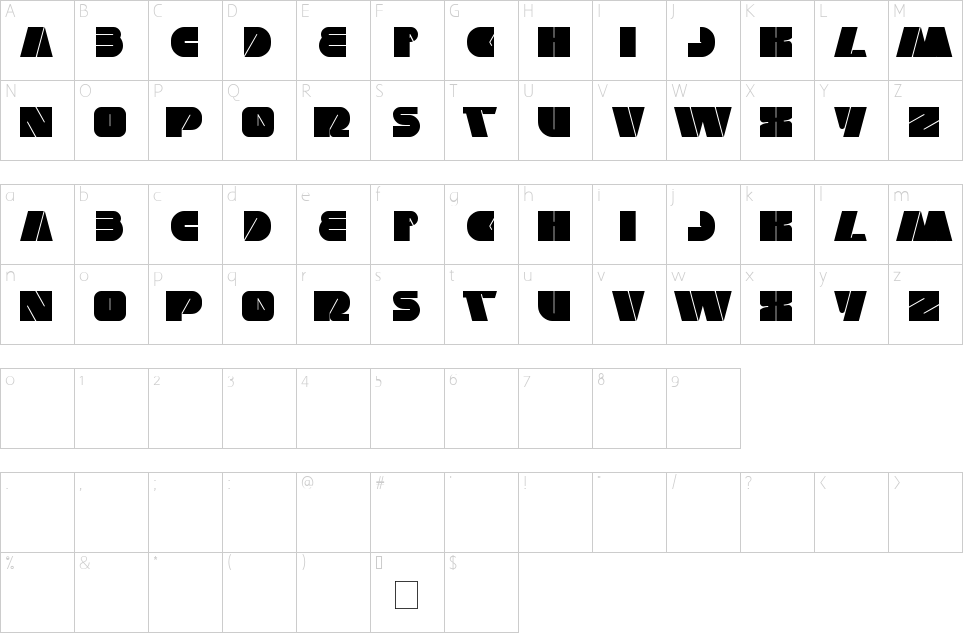
A fonte Monster Rock é uma escolha perfeita para designers que desejam um estilo poderoso e irreverente para seus projetos. Inspirada em rock, essa fonte garante um tom inovador e inconfundível em qualquer projeto. Desenvolvida pelo designer desconhecido weknow, Monster Rock é atualmente uma das fontes mais baixadas, já sendo instalada por mais de setecentos e duzentos e quatorze pessoas. Perfeita para adicionar um toque único e vibrante a qualquer projeto, essa fonte traz personalidade e estilo para textos e headlines. Se você está procurando por uma fonte que se destaca em sua coleção, a Monster Rock é uma escolha excepcional.